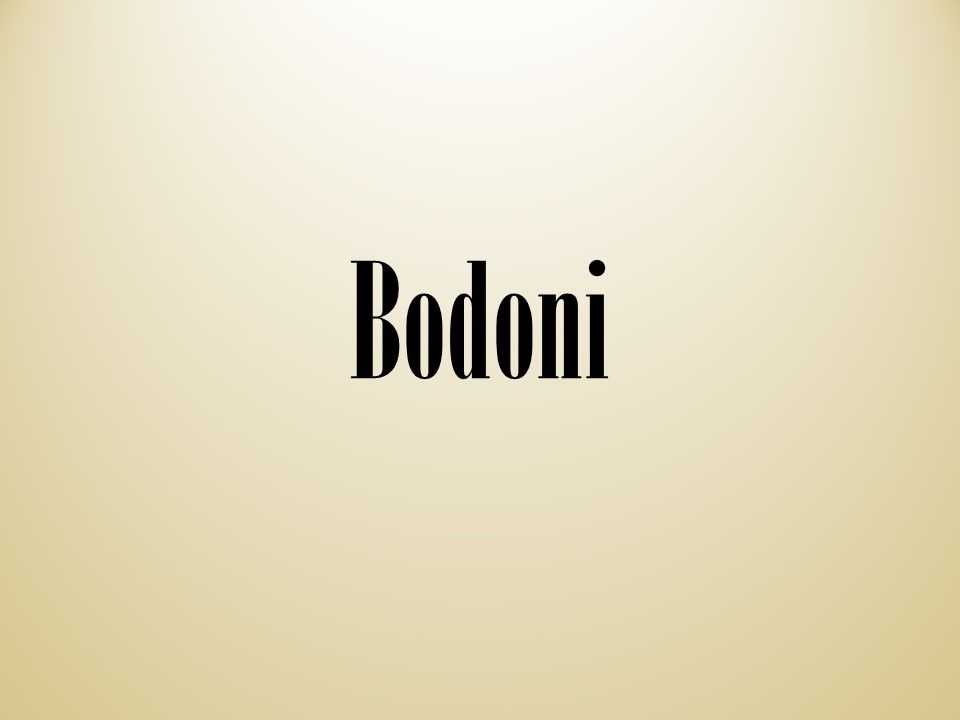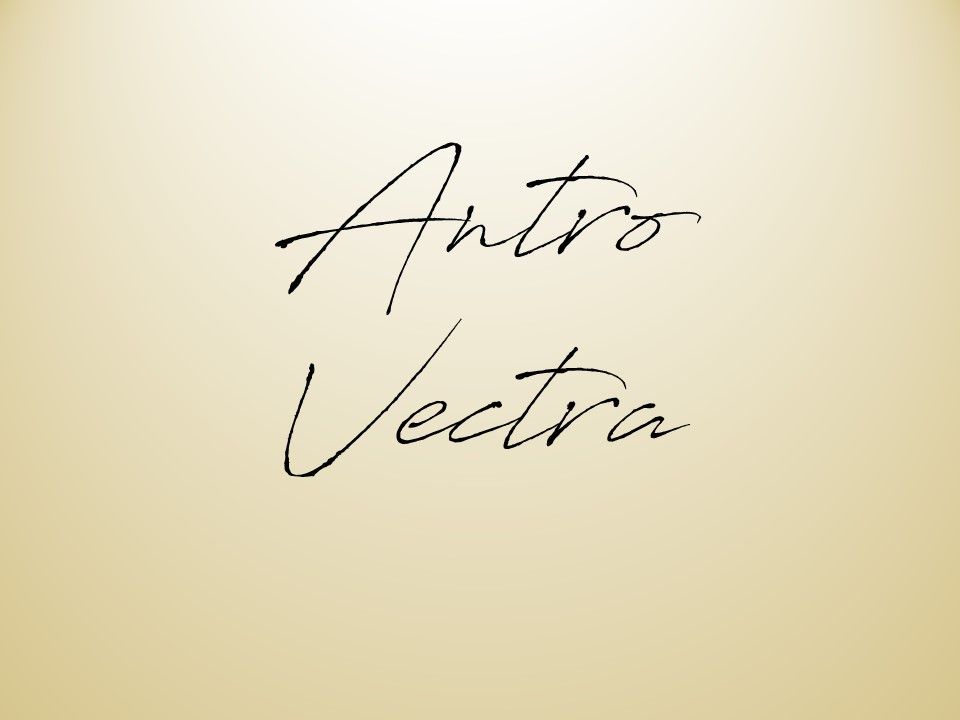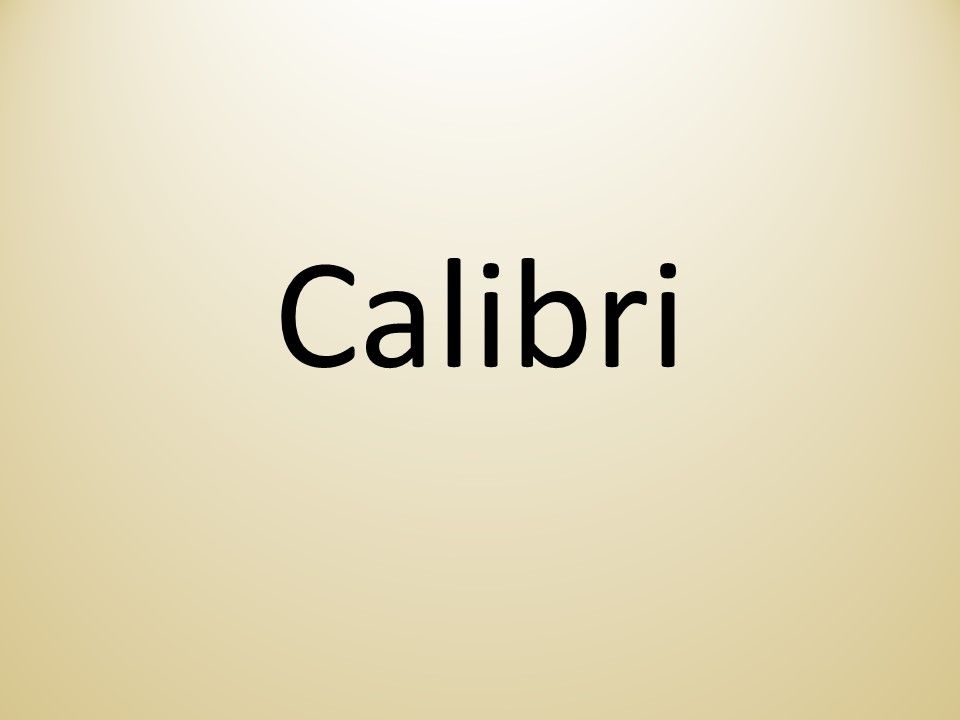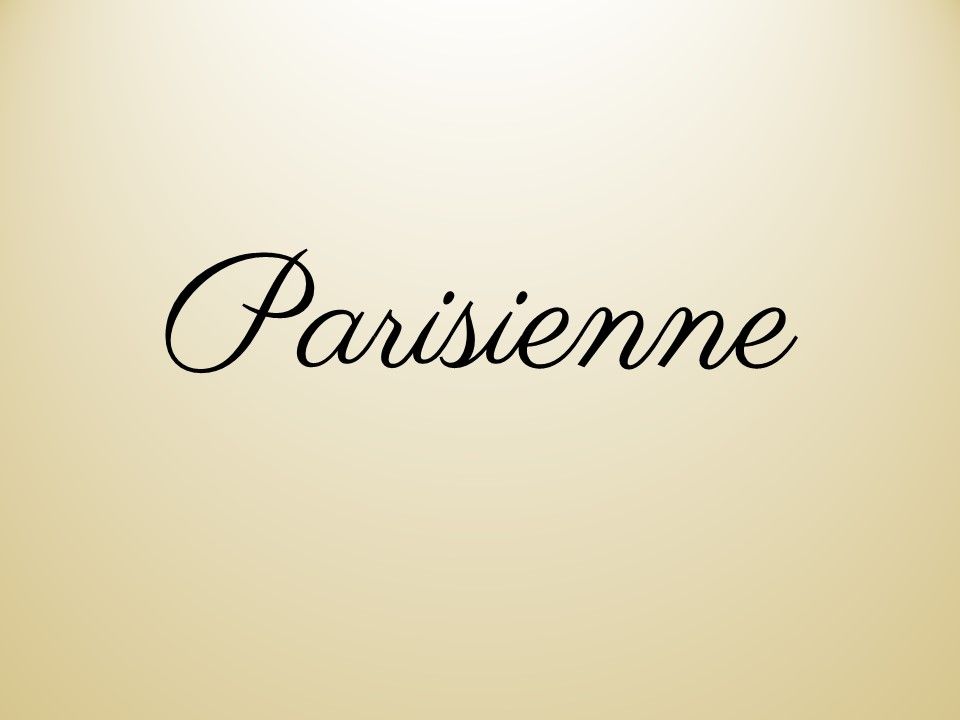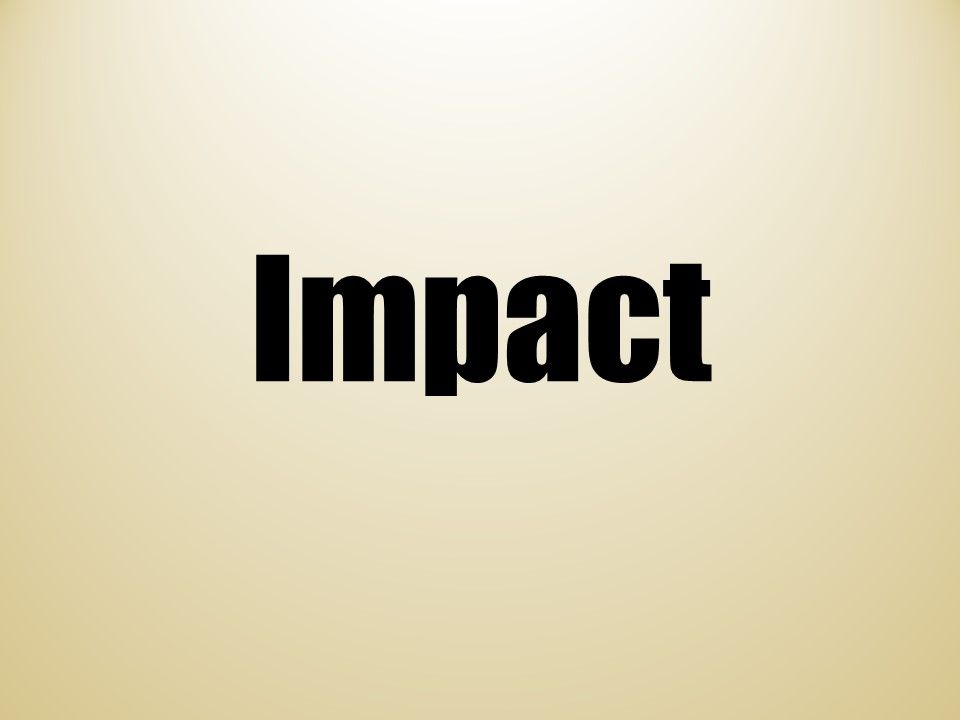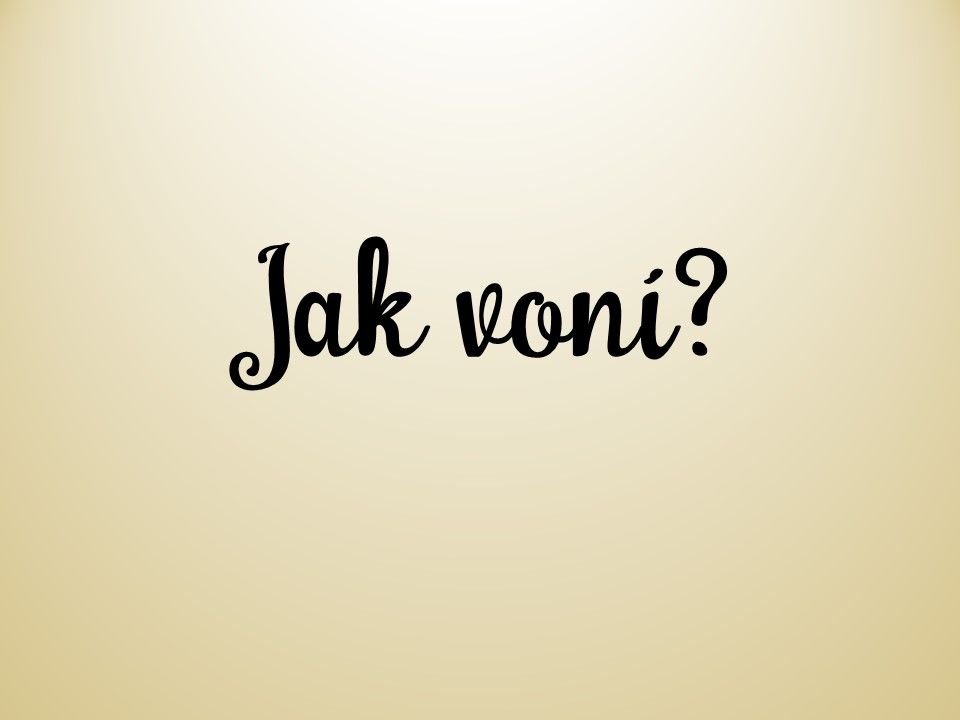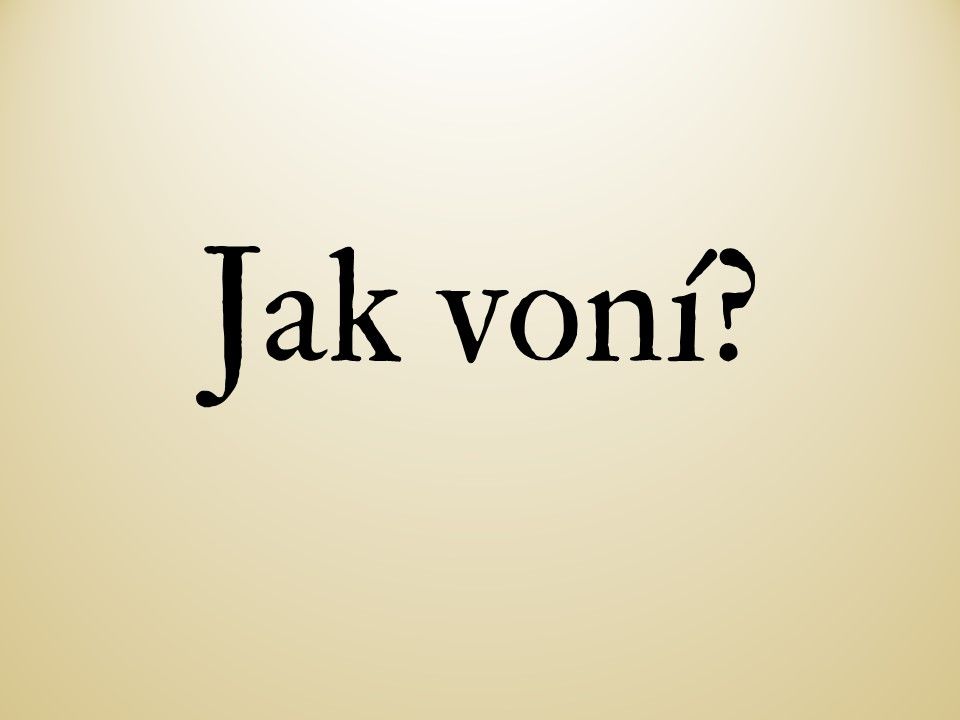
Dovedete si představit, jak často změníte své rozhodnutí na základě fontů? Denně asi 100x.
Dobře, možná přeháním, ale do desítek malých rozhodnutí to půjde. Každou chvilku našeho dne se dostáváme na malá rozcestí, na kterých stojí drobné ukazatele, které nás posílají buď napravo, nebo nalevo anebo nám řeknou jednoduše STOP, tudy cesta nevede.
A jedním z těch ukazatelů je jednoznačně písmo, nebo spíš použitý FONT (záleží totiž hodně i na tučnosti nebo řezu, jaký u písma použijete).
Vždy, když jdete po ulici, útočí na vás fonty na všech vývěsních štítech. A online to není o moc lepší.
Vyberete si pekárnu, která má chutně plný, vřelý nápis, který vás vede dovnitř k vůni koláčů, nebo půjdete o ulici dál do pekárny s patkovým old school fontem, kde to voní klasickým řemeslem francouzských baget a křupavého chleba?
Možná se rozhodnete podle nálady, ale určitě cestou minete tu obyčejnou nevýraznou pekárnu, která má na štítu písmo, kterým by mohlo být napsané i „samoobsluha“.
Udělala jsem vám chutě? A o tom to přesně je! Když máte chuť, když vnímáte pocity, emoce přebírají vládu nad rozumem.
Rychlejší je předat je jinými smysly.
Od toho máme 5 smyslů a je velká škoda v textu využívat jenom jeden!
Víte o tom, že…
fonty vám mohou zprostředkovat vůně? Jsem si jistá, že 90% z vás se shodne na tom, které písmo pasuje k lehké letní citrusové vůni , které k těžkému pánskému parfému a které k přeslazené voňavce z drogerie.
Víte i o tom, že…
fonty fungují přesně jako oblečení? Dokážete je dokonce cítit mezi prsty, jakou mají asi strukturu. Arial a Calibri jsou konfekční hadry, Antro Vectra rozevlátý šifónový šál a takový Vollkorn, to je kvalitní tvíd na nezničitelné pánské sako, jaké nosil můj dědeček i do dílny. Klidně se záplatami na loktech. A Bodoni, to jsou malé černé pro Audrey Hepburn.
A napadlo vás někdy, že…
fonty mohou dodávat textu atmosféru, úplně jako hudba ve filmu? Slyšíte ji, a už víte, co přijde za zápletku. Font dokáže to samé, když je dobře vybraný, umí udělat z textu zážitek a doplnit ho o další rozměr, díky kterému text vnímáme daleko intenzivněji, rozezní v nás jiné struny. Cítíme romantiku, strach, péči nebo nátlak. Zkuste si to, u kterého písma slyšíte „ I Will Always Love You“ a u kterého rock?
Každý den, každou hodinu, každou minutu si vybíráme podněty, které nám jsou příjemné. Které jsou v souladu s tím, jak se právě cítíme, co potřebujeme a s kým se chceme bavit. A v podnikání, tam je to ještě jiný level. Font, který vyberete přímo ovlivní to, jak se při čtení budou vaši čtenáři (a potencionální zákazníci) cítit.
A podle toho, jak se budou cítit, se co? Rozhodnou. Úplně stejně, jako se my všichni rozhodujeme každý den na našich malých rozcestích. Dobrá zpráva je, že se můžete naučit používat fonty vědomě, vybírat takové, které budou mluvit za vás. Ušetří vám to spoustu práce i nedorozumění.